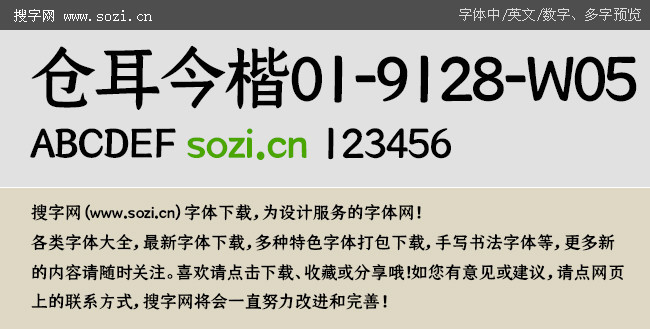
倉(cāng)耳今楷01-9128-W05
搜字網(wǎng)給大家提供一款倉(cāng)耳今楷01-9128-W05中文字體下載,倉(cāng)耳今楷從筆形、布白、結(jié)體、排版四個(gè)方面進(jìn)行了深入研究,呈現(xiàn)出舒適的閱讀效果。適合應(yīng)用于藝術(shù)設(shè)計(jì)、平面宣傳設(shè)計(jì)、網(wǎng)頁(yè)設(shè)計(jì)等應(yīng)用。(本字體為個(gè)人非商用版,如需要商用請(qǐng)聯(lián)系官方購(gòu)買(mǎi)版權(quán))
- 風(fēng)格類(lèi)別: 楷體